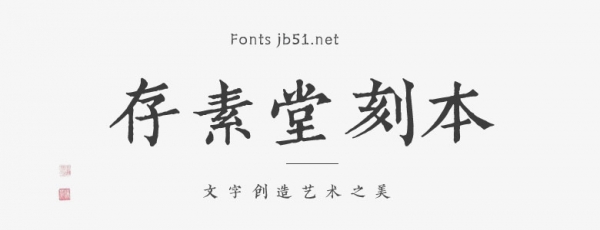
存素堂是文集的名稱(chēng),也是藏書(shū)的堂號(hào)。存素堂刻本簡(jiǎn)體源自清代刻本風(fēng)格,在刀篆的基礎(chǔ)上,字勢(shì)銳利如絲,妙筆如畫(huà),流暢生花。它的筆劃之間盡在還原毛筆書(shū)寫(xiě)的俊逸灑脫,給人一種豪放的文士風(fēng)度之美。如果將它運(yùn)用于現(xiàn)代散文詩(shī)歌、品牌海報(bào)、宣發(fā)文稿上,不論是作為標(biāo)題或者正文,都會(huì)具有強(qiáng)烈的視覺(jué)沖擊感。